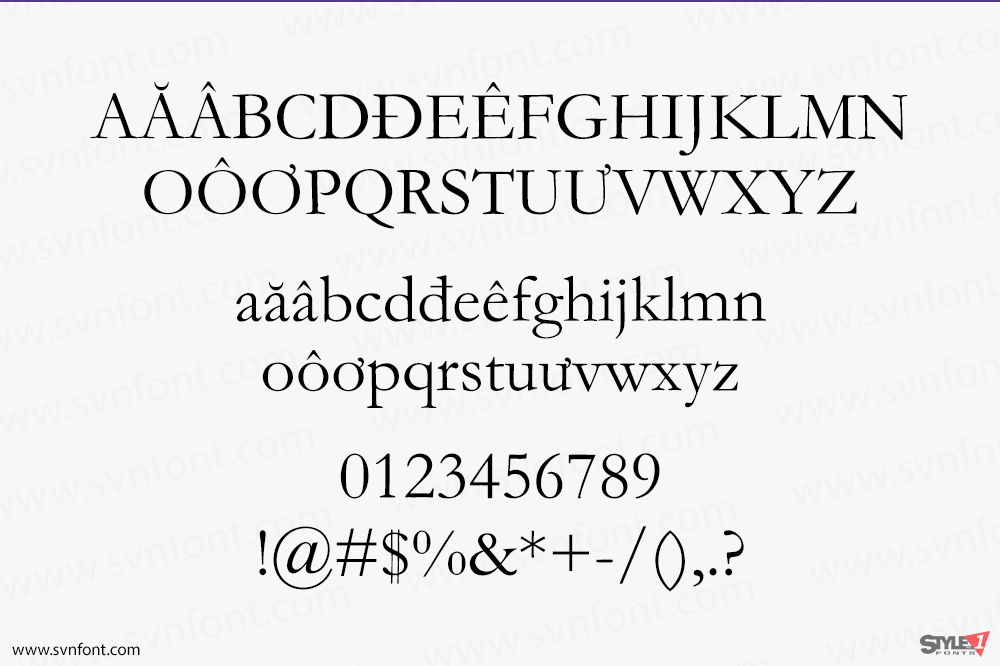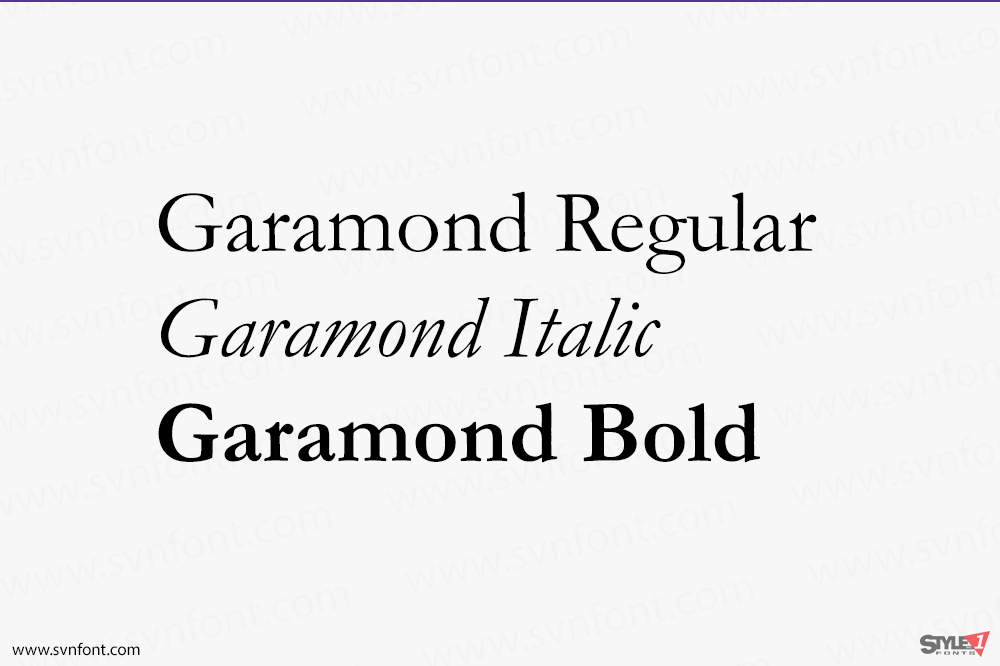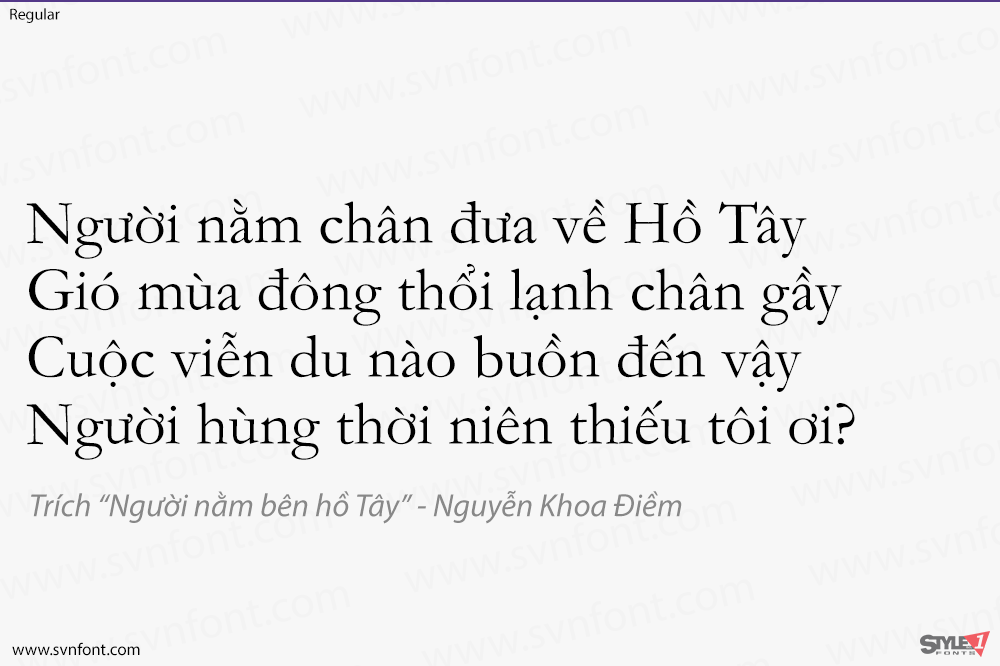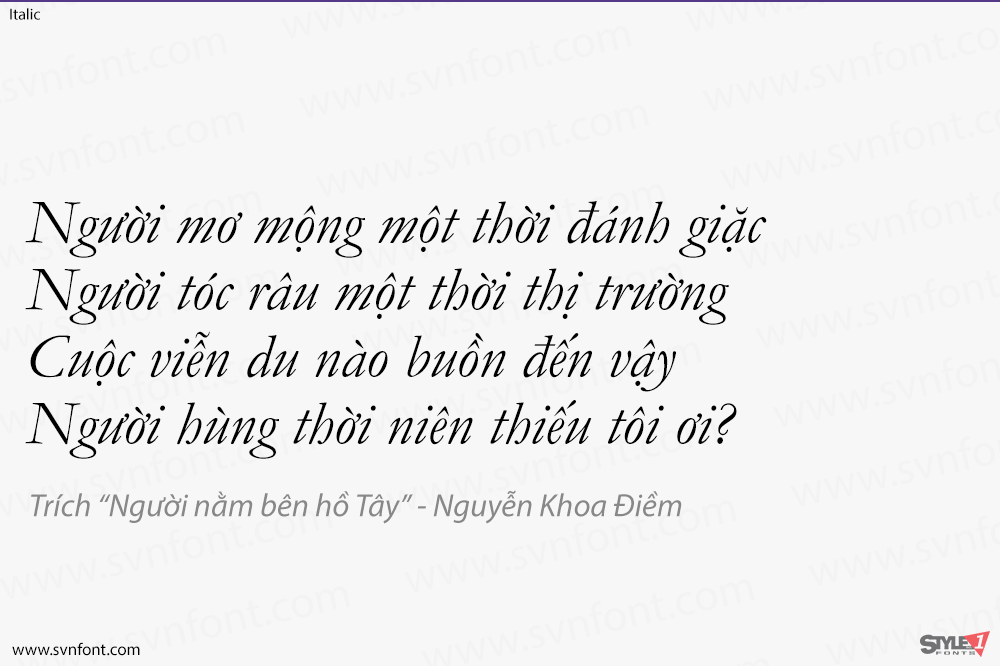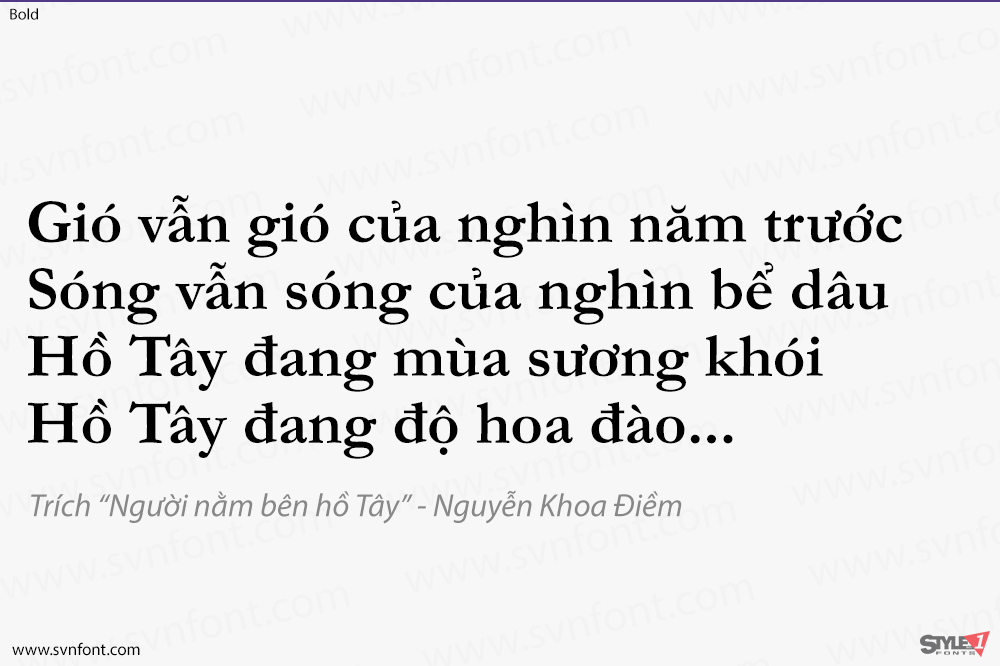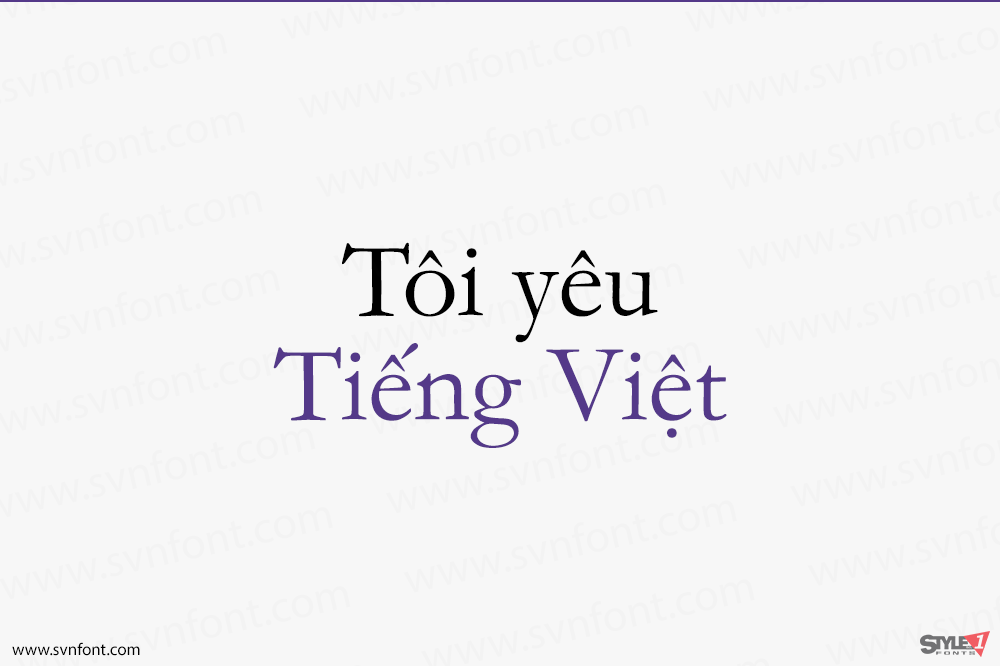
Monotype Drawing Office 1922. Kiểu chữ này dựa trên các kiểu chữ La Mã được Jean Jannon khắc vào năm 1615. Jannon đã theo sát các thiết kế của Claude Garamond, vốn đã được khắc vào thế kỷ trước. Các kiểu chữ của Garamond, đến lượt mình, lại dựa trên những kiểu chữ được Aldus Manutius sử dụng vào năm 1495 và được Francesco Griffo khắc. Kiểu chữ nghiêng (italic) dựa trên các kiểu chữ được khắc ở Pháp vào khoảng năm 1557 bởi Robert Granjon. Garamond là một kiểu chữ đẹp mắt với vẻ ngoài thân mật, trông rất tốt trong nhiều ứng dụng khác nhau. Nó đặc biệt phù hợp trong sách và các cài đặt văn bản dài.
Nhà thiết kế: Claude Garamond